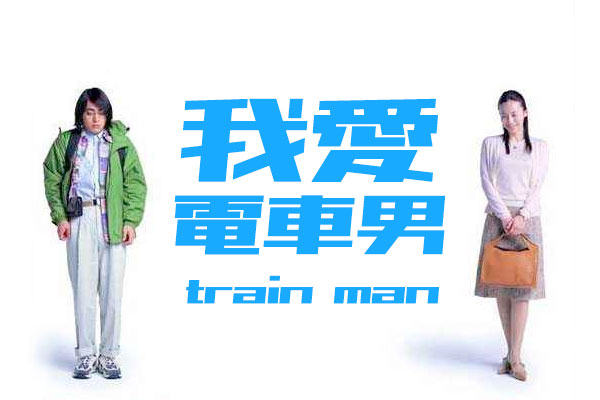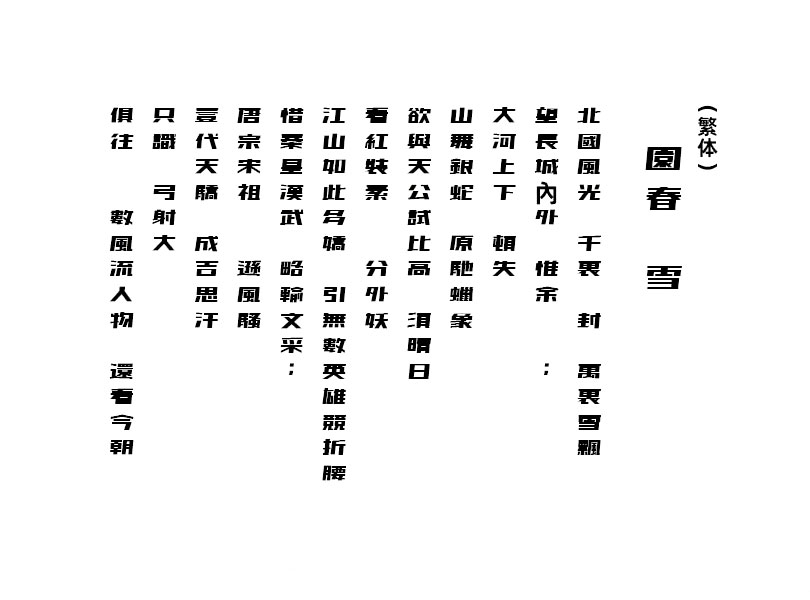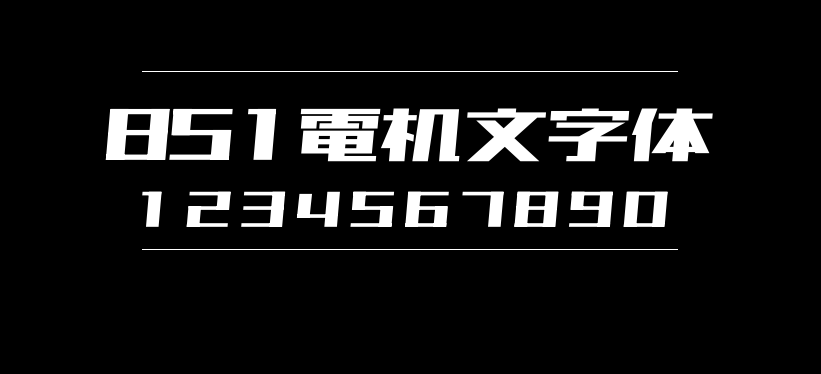
851电机文字体
851电机文字体(851Gkktt、851ゴチカクット)是一款充满锐利感的刚性字体,跟我们国内的站酷高端黑、优设标题黑的风格相类似,它有一定倾斜角度,看上去有速度感。竖画倾斜5°,目前收录平假名、片假名、数字、JIS第1水准汉字+人名用汉字等。虽然支持的中文文字还不够多,但是现在作者目前还在继续开发中(最后更新于2019年9月),期待能像851手写杂书体那样,支持更多的中文字体。
851电机文字体